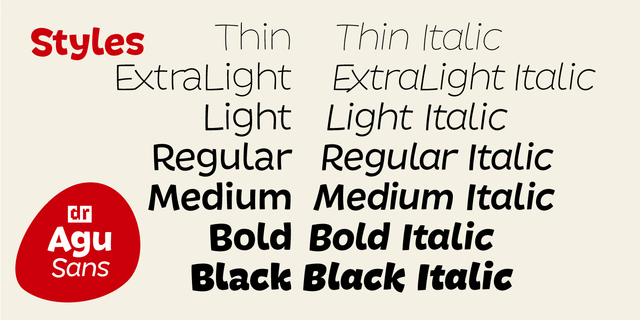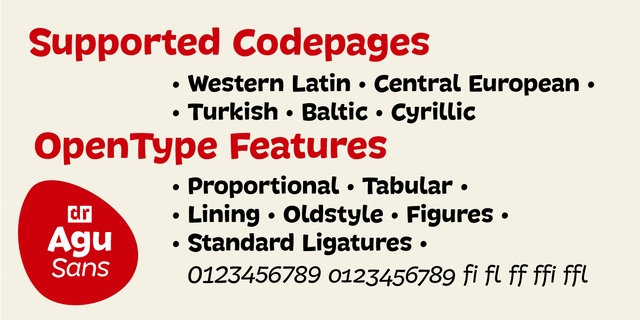
Агу Санс – это шрифтовое семейство с набором прямых и курсивных начертаний от сверхсветлого до сверхжирного. Может применяться для неформальных текстов, детских книжек и приложений. Шрифт разработал Дмитрий Растворцев в 2012 году.
веселый, задорный, смешной, дружелюбный, добродушный, добрый, радостный, прыгающий, неряшливый, игривый, приветливый, озорной, непоседливый, подвижный, оригинальный, свежий, тонкий, легкий, детский, наивный, невесомый, прозрачный, нежный, воздушный, проволочный, динамичный, худой, счастливый, летний, карикатурный, милый, мультяшный, остроумный, домашний, симпатичный, спелый, вкусный, тяжелый, заметный, броский, новогодний, яркий, активный